字体是浓缩的视觉符号,也是一种国际语言。一款好的字体在设计中会起到使人过目不忘、百看不厌的效果。字体是实现与形态的完美结合,可以引起人们丰富的想象。作为商业用途选择一款合适的字体绝对是重中之重。接下来我们一起看看下面这些商业用途锦上添花的图片字体吧?
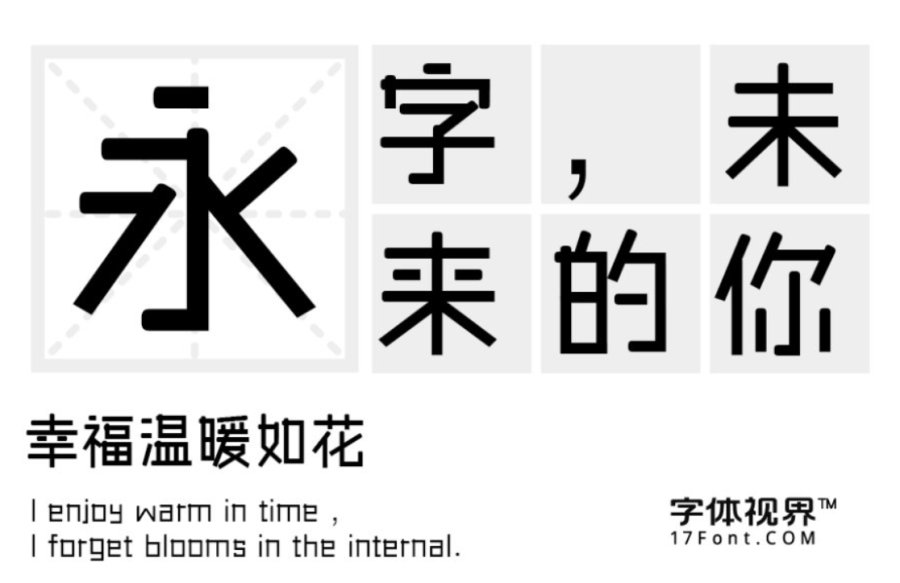
三极傻黑简体:这是一款几何型构成的作品。整体风格率真,直接。字体稳重简洁,笔画平直、粗细匀称,起笔为圆头温柔可爱,收笔平直天真率气,又有强烈的个性。风格年轻、富有亲和力。它的灵感来源于管状物体,直接简单,坚韧不屈,给人一种直接干练的感觉。
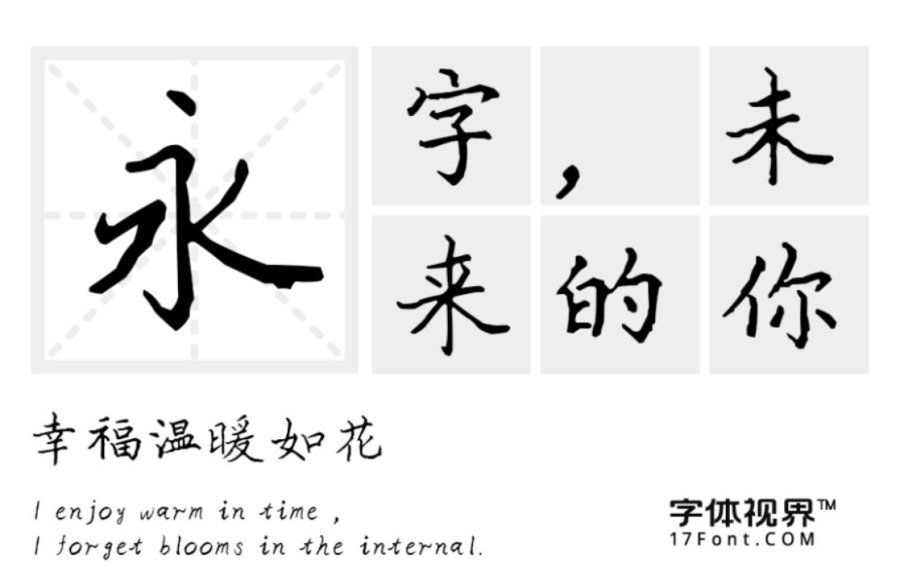
三极毛哥楷书:这款三极毛哥楷书结构严谨,既有颜体的雄浑,又不失赵体的飘逸。严谨秀气而从容和优雅,让人赏心悦目,百看不厌。可广泛应用于书刊、广告、包装、影视以及社交网络个性化用字。
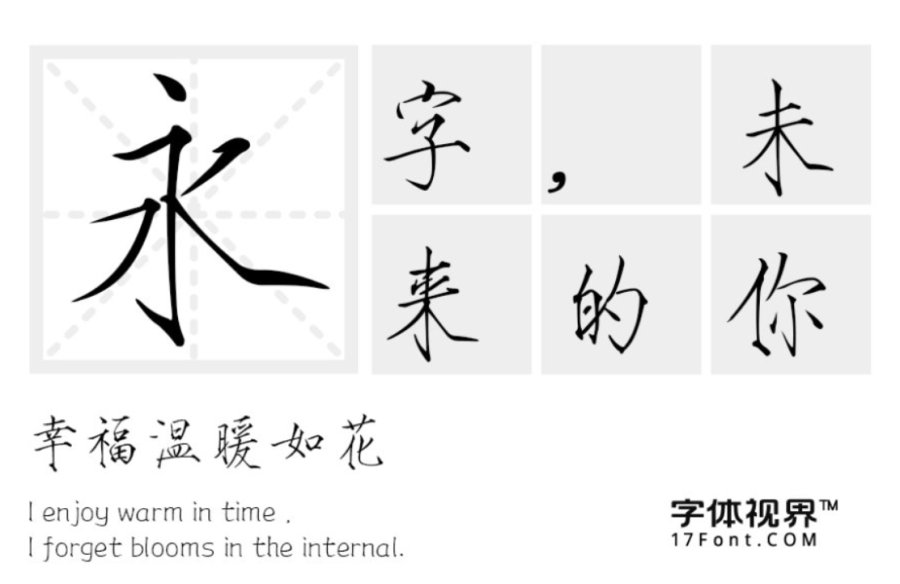
三极瘦金简体:这款字体源自宋徽宗书法字体。这款字体的笔画纵横飘逸,狭瘦挺拔。横画收笔带钩,竖画收笔带点。整个字面狭长,中宫偏小,重心稳定。适用商业类广告和产品包装设计及店面设计。